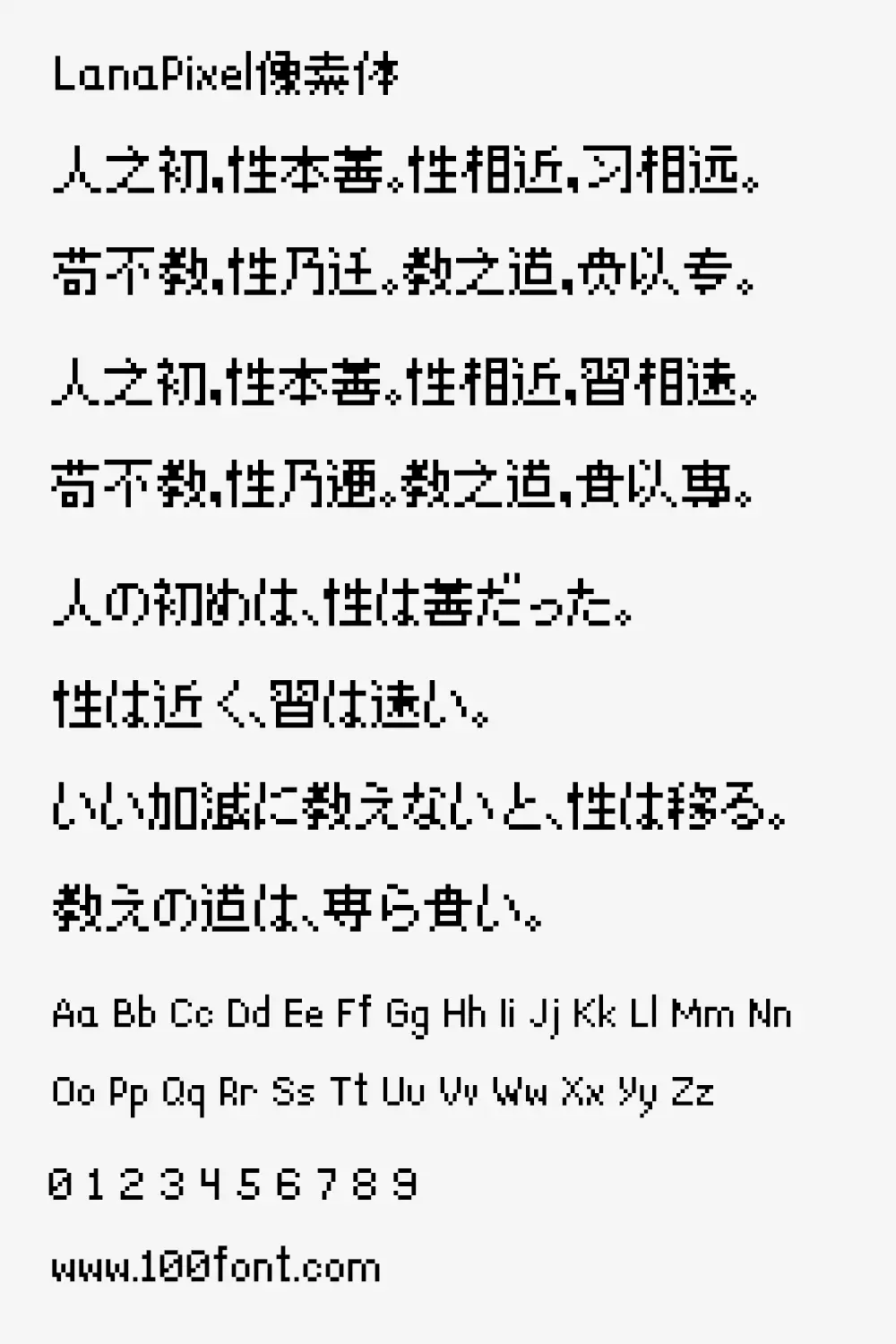
LanaPixel是一款用於本地化像素藝術遊戲的位圖字體。 包含大約 19400 個字符,支持大多數現代歐洲語言(拉丁語、希臘語、西里爾文)、土耳其語(拉丁語)和韓語(韓文),很好地支持日語和簡體中文,並支持繁體中文。拉丁文、希臘文和西里爾字符具有字距調整。
但是,請注意,雖然支持許多CJK(中文,日語,韓語)字符,但由於體積小,其中許多字符幾乎難以辨認,因此需要非常小心地使用此字體以確保易讀性並避免視覺上覆雜的字符。使用較大的字體將是更簡單的選擇。
此字體設計為以 11px 顯示。由於這是一種像素字體,建議僅按整數量(1x 或 11px、2x 或 22px、3x 或 33px...)縮放以避免失真。
A bitmap font for localizing pixel art games.LanaPixel contains approximately 19400 characters, with support for most modern European languages (Latin, Greek, Cyrillic), Turkish (Latin), and Korean (Hangul), good support for Japanese and Simplified Chinese, and decent support for Traditional Chinese. The Latin, Greek, and Cyrillic characters have kerning.
However, please note that while many CJK (Chinese, Japanese, Korean) characters are supported, many of them are nearly illegible due to the small size, and thus this font needs to be used very carefully to ensure legibility and avoid visually complex characters. Using a larger font would be the much easier option.
This font is designed to be displayed at 11px. As this is a pixel font, it is recommended to only scale by integer amounts (1x or 11px, 2x or 22px, 3x or 33px...) to avoid distortion.